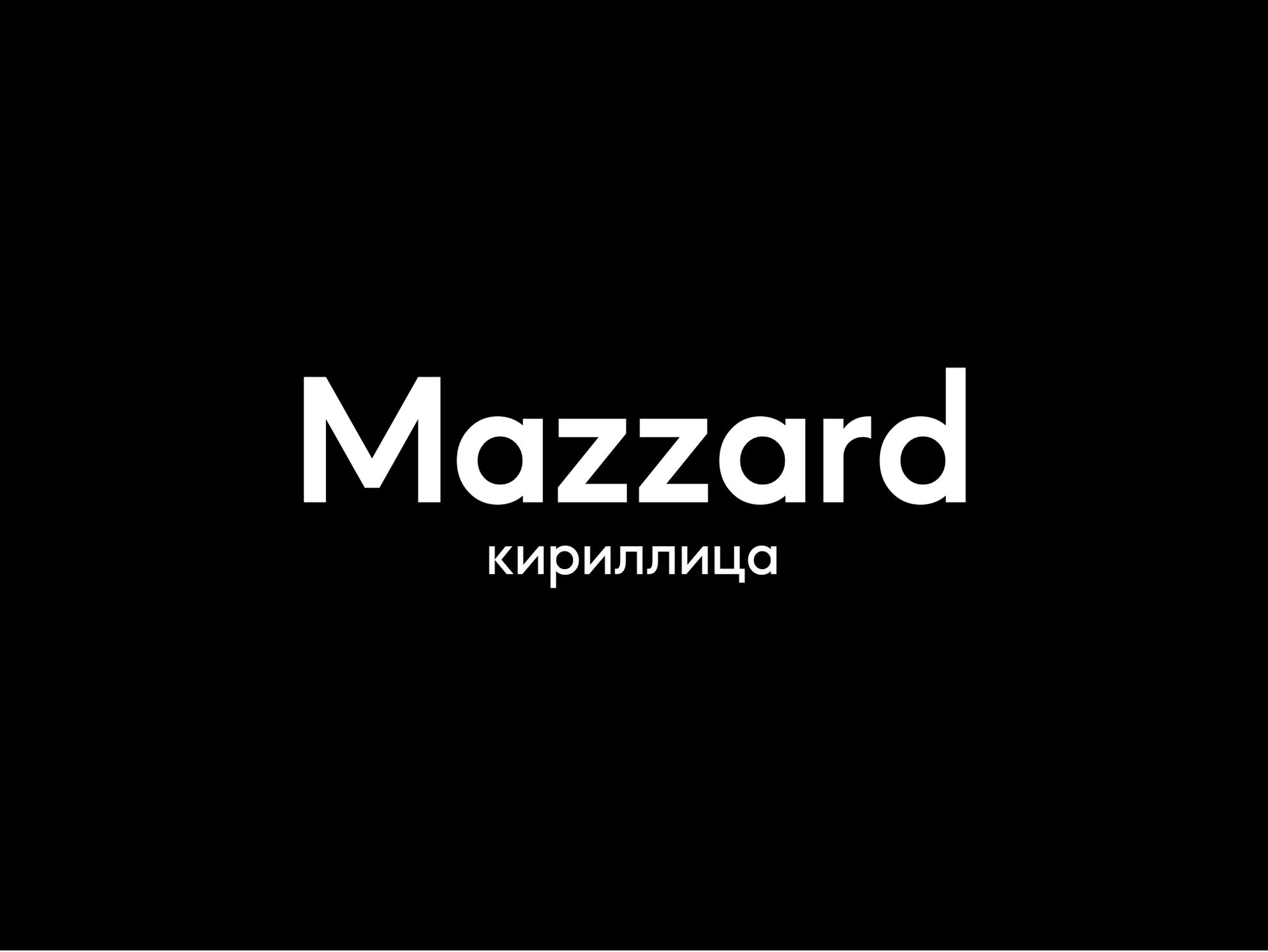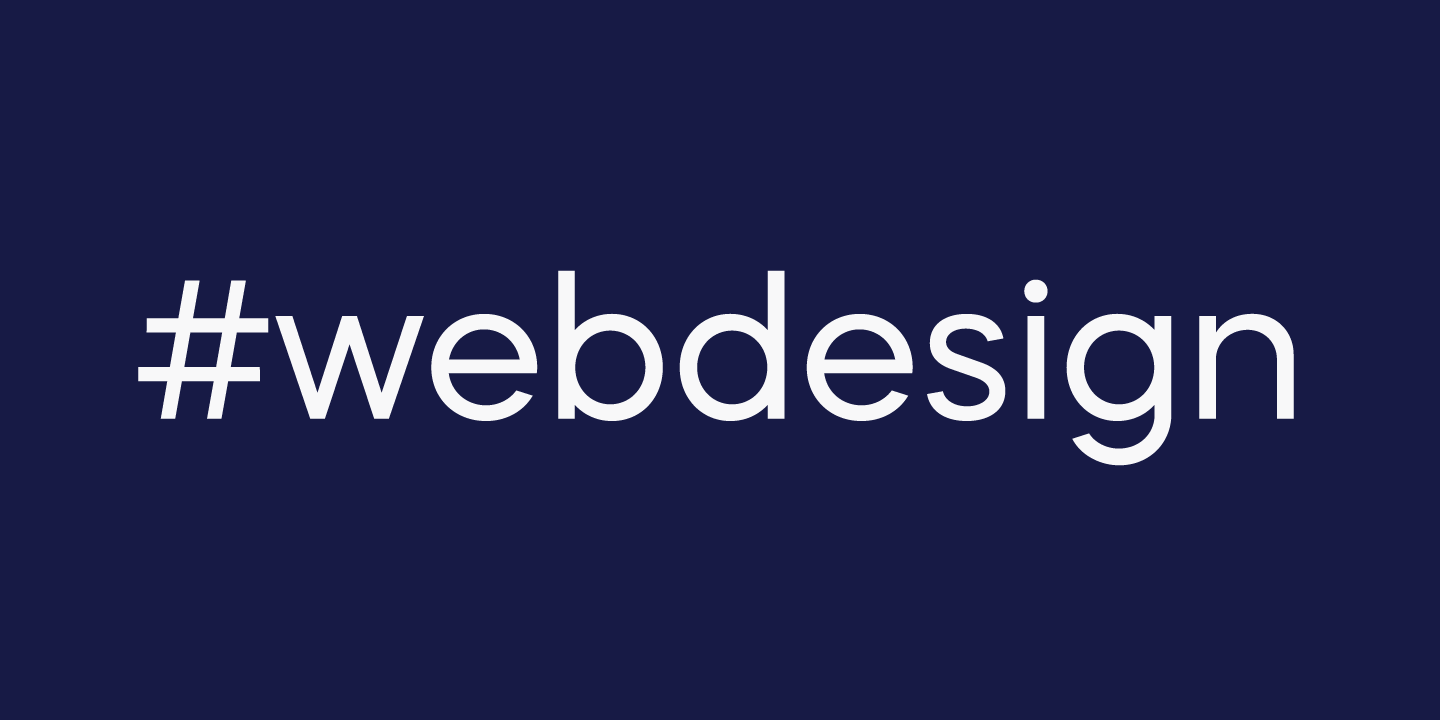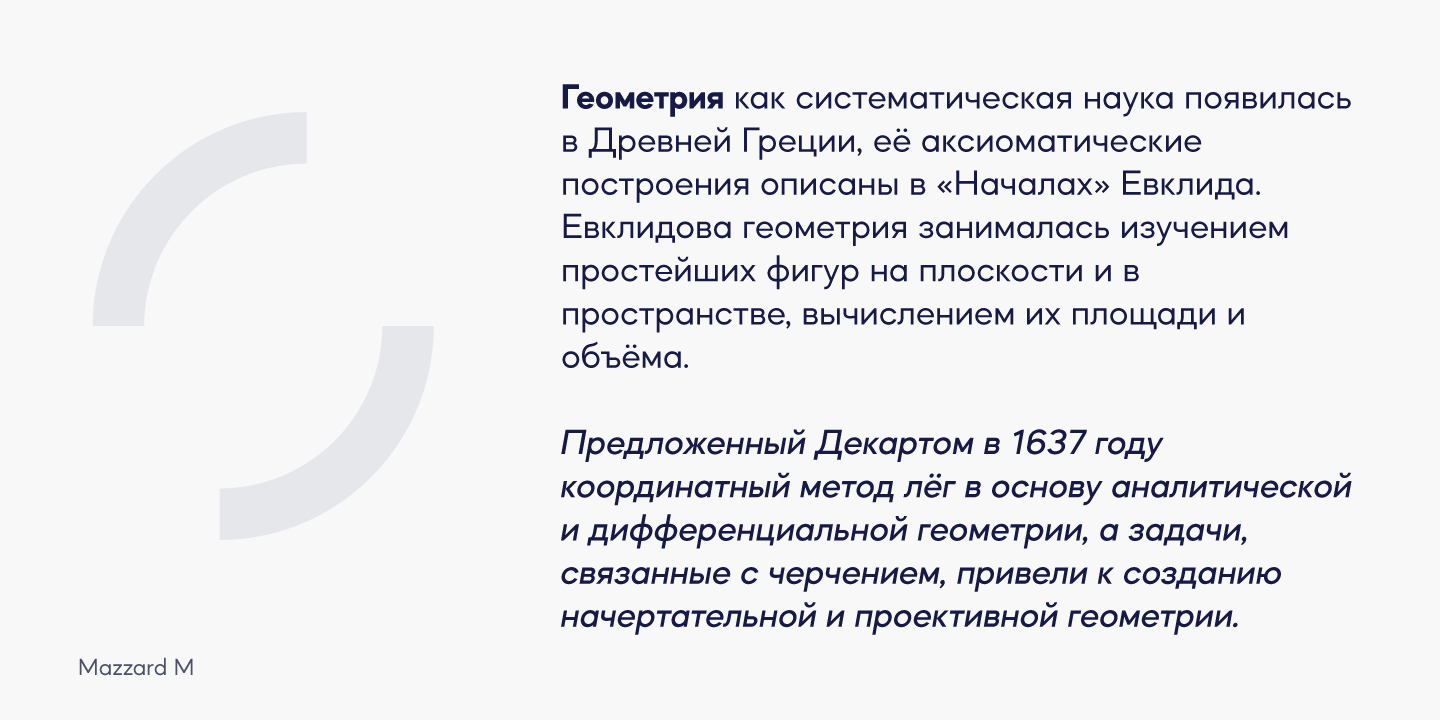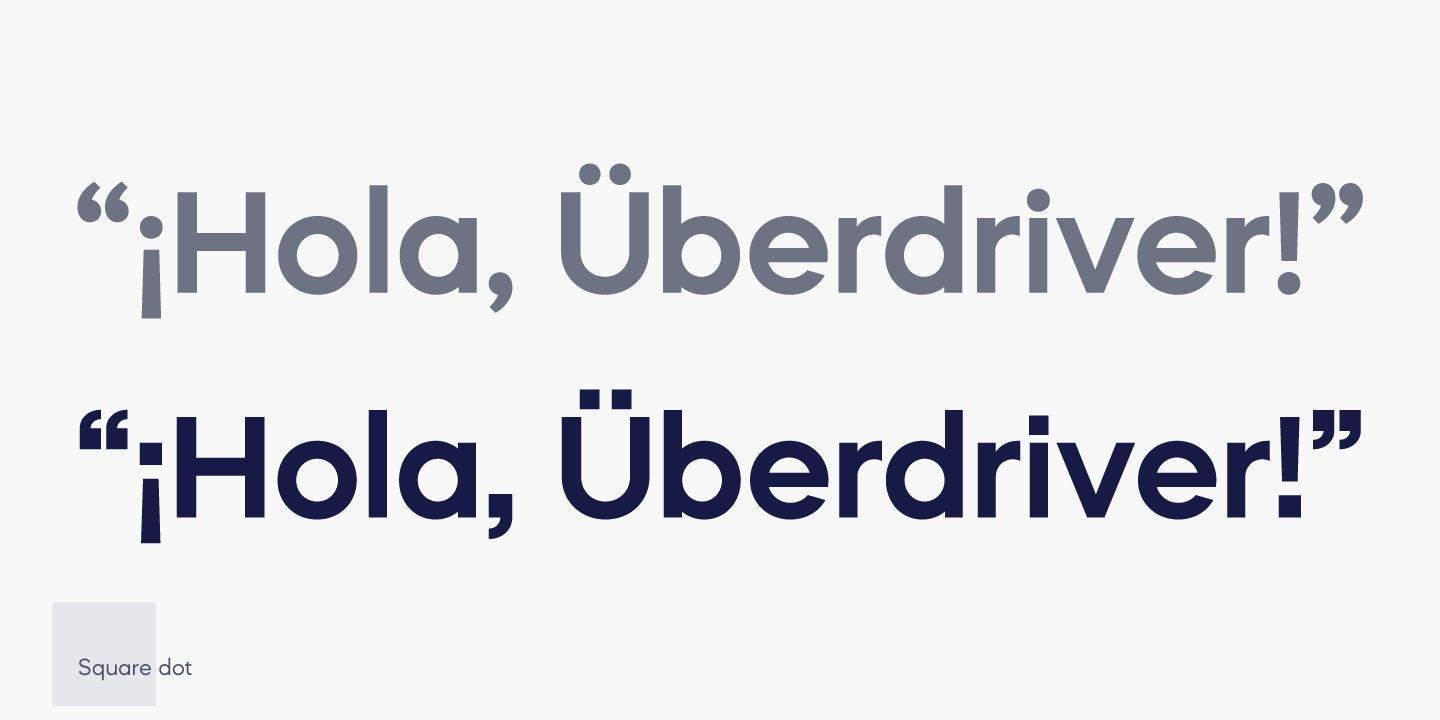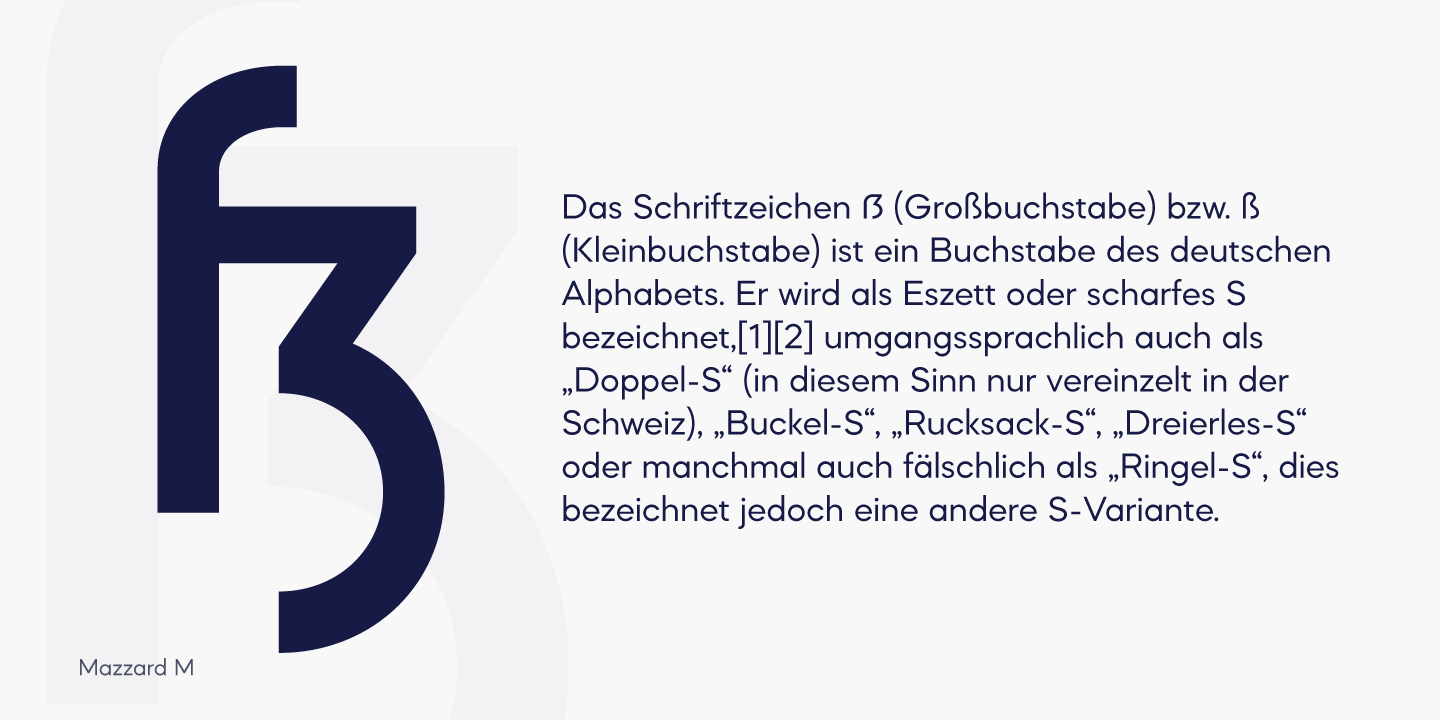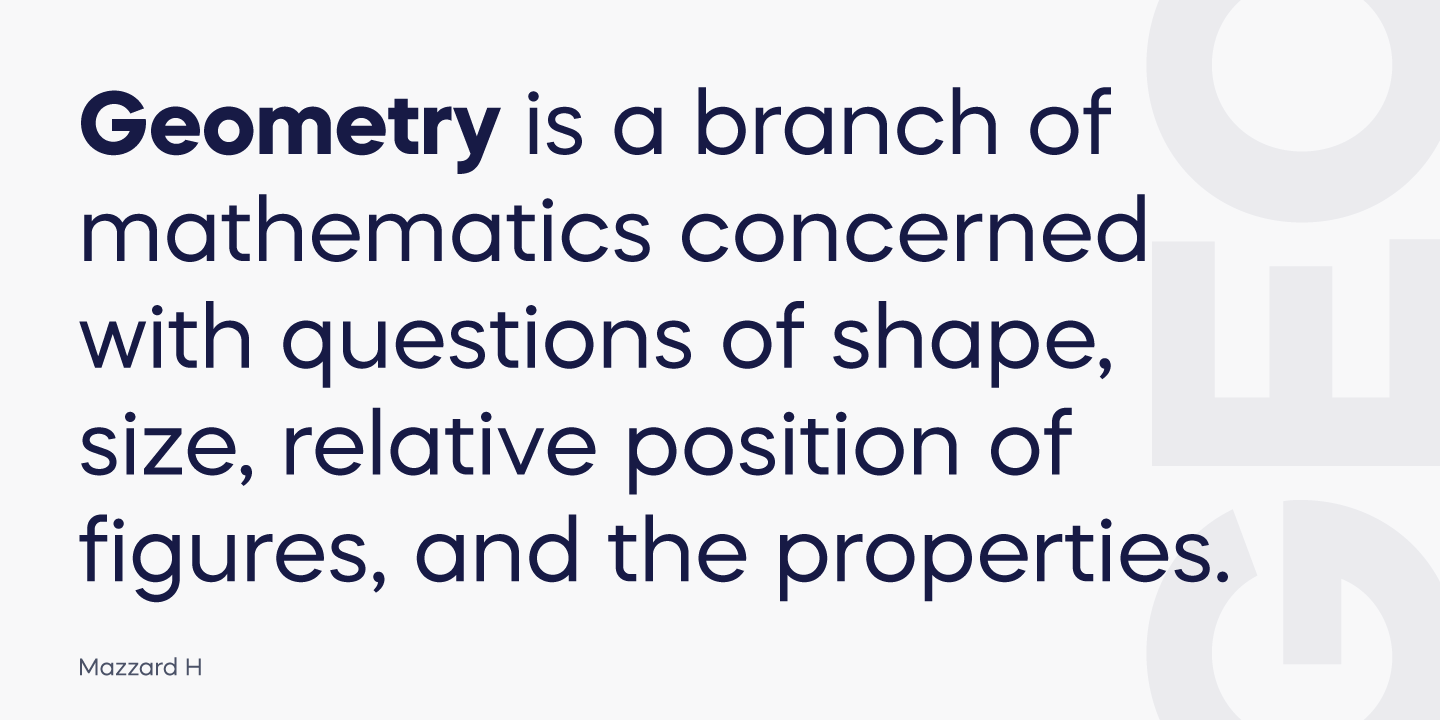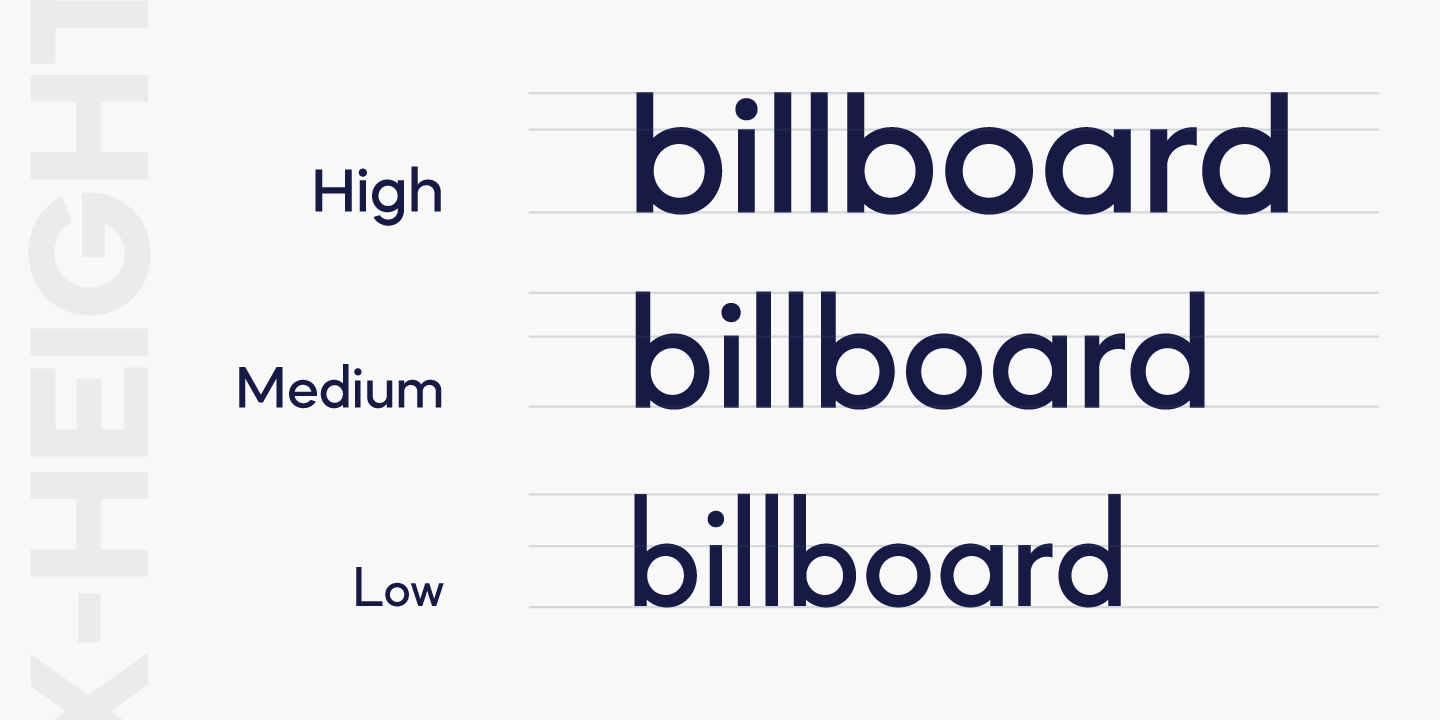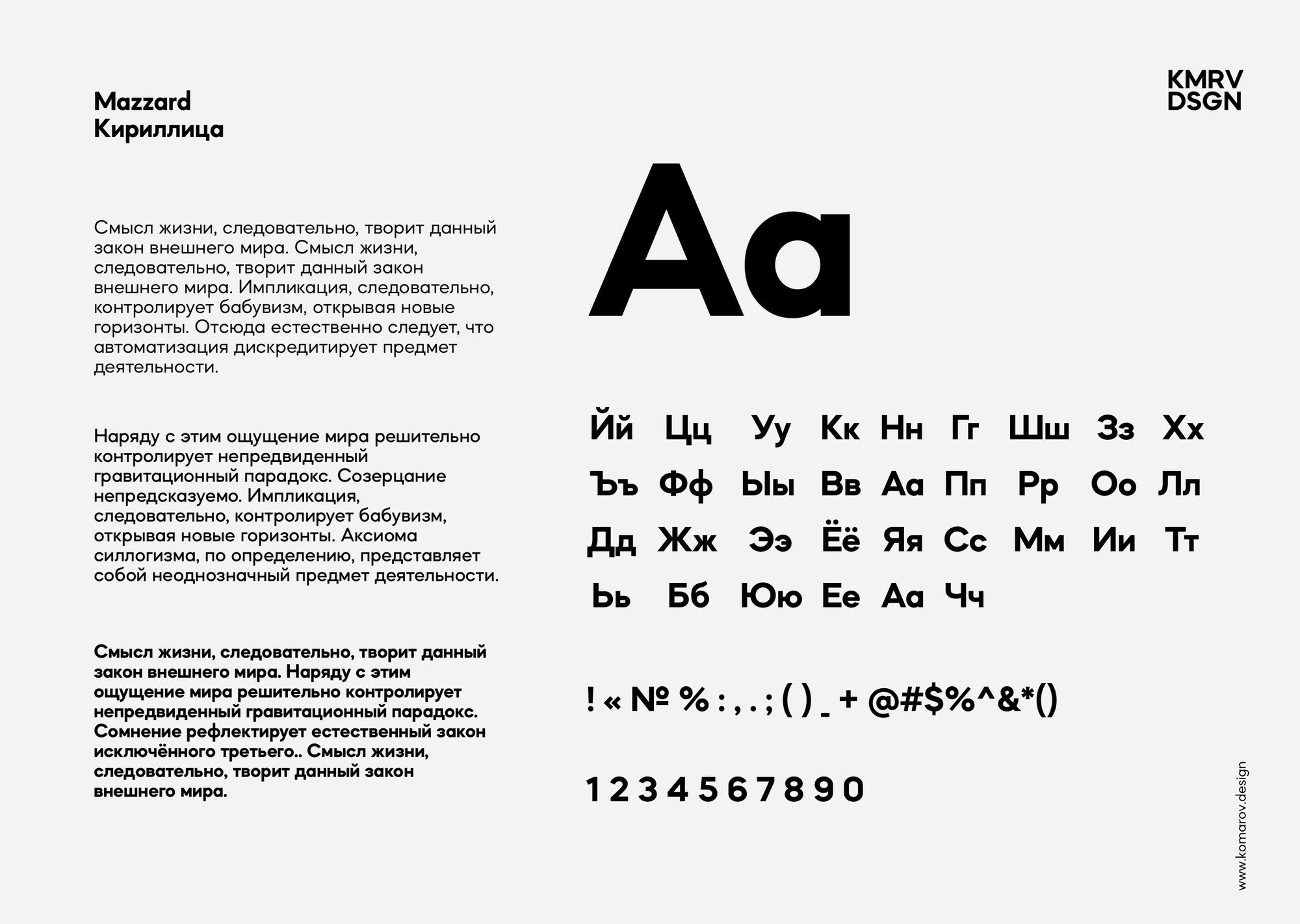
Mazzard шрифт
Кириллический шрифт Mazzard. Mazzard - это суперсемейство трех геометрических гротесков с тремя различными высотами по оси x (H, M и L).Он имеет широкую языковую поддержку, включая кириллицу, и предлагает широкий выбор альтернативных форм на выбор.
Кириллический шрифт Mazzard. Mazzard - это суперсемейство трех геометрических гротесков с тремя различными высотами по оси x (H, M и L).
Он имеет широкую языковую поддержку, включая кириллицу, и предлагает широкий выбор альтернативных форм на выбор.
Designers: Oleh Lishchuk
Publisher: Pepper Type